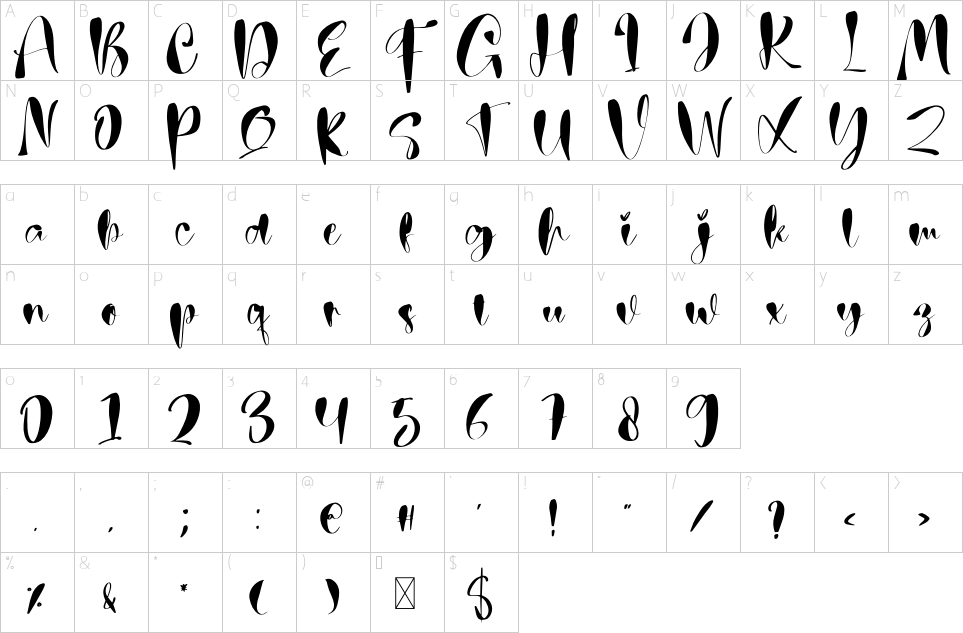
A fonte Midnight Font é uma opção única e elegante para seus projetos digitais, especialmente para designers buscando um estilo único e intrigante. Desenvolvida pelo designer desconhecido, Midnight oferece um tom suave e misterioso, perfeito para qualquer design que deseje transmitir uma atmosfera sombria e envolvente. Com uma aparência moderna e fácil de usar, esta fonte é um excelente complemento para qualquer projeto gráfico. Desenvolvida para Windows e Mac, a Midnight Font já foi baixada 478 vezes, demonstrando seu valor e popularidade entre os designers. Não perca esta oportunidade para dar um toque especial a seus projetos com uma fonte que criará uma verdadeira sensação de misticismo e elegância.